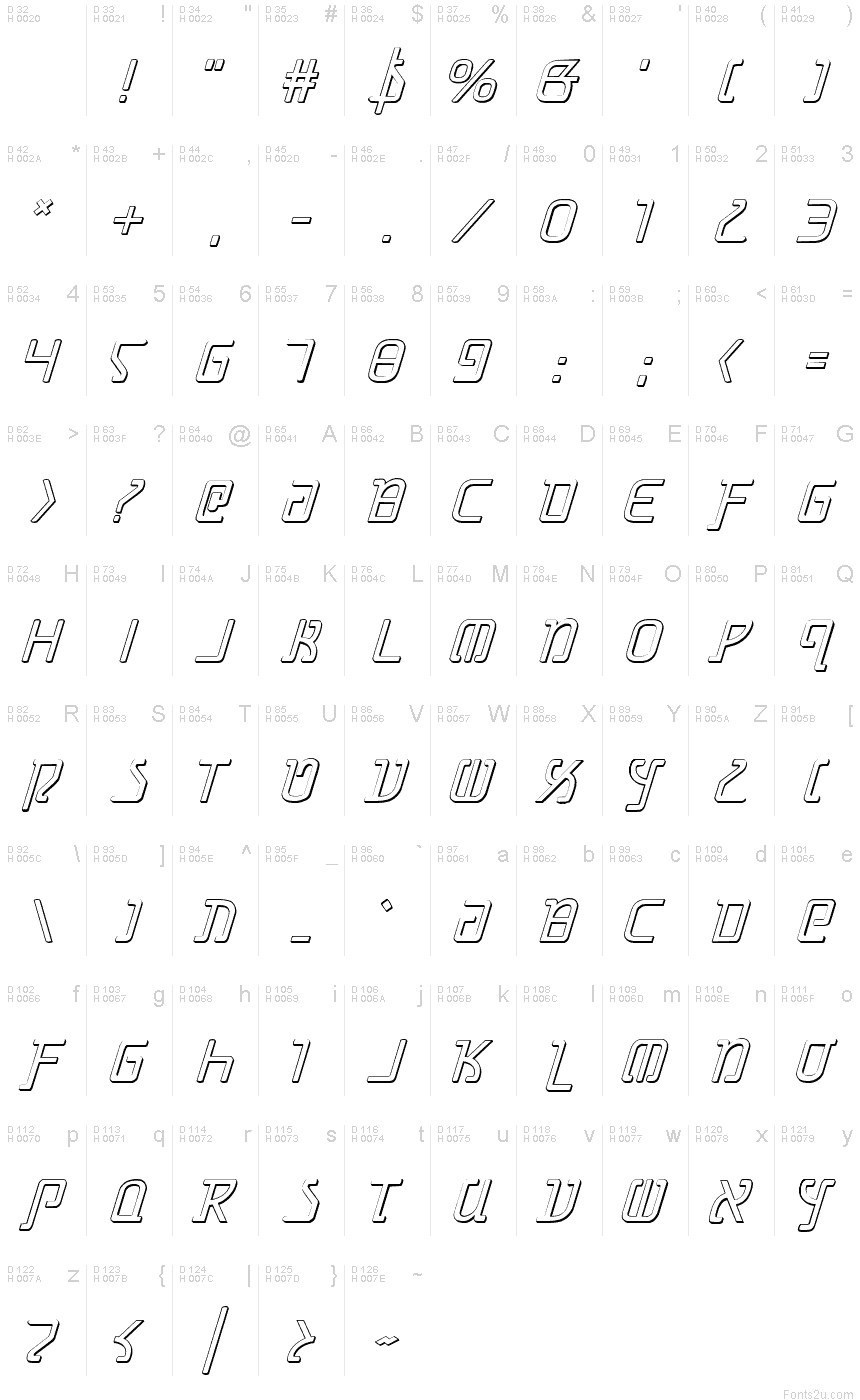
Grimlord Shadow Italic autorstwa Iconian Fonts to darmowy krój pisma typu display o konturowej budowie, z mocnym pochyleniem do przodu i retro-futurystycznym wyglądem science-fiction. Puste w środku litery, ścięte narożniki i kanciaste łuki tworzą opływową, mechaniczną sylwetkę.
Sporty motorowe i futurystyczna technologia to jej najbardziej oczywiste motywy. Konturowa konstrukcja sprawdza się na plakatach wyścigowych, w grafikach gier z automatów oraz w gadżetach science-fiction, gdzie litery mogą przypominać spersonalizowane emblematy pojazdów lub oznaczenia interfejsu. Najbardziej przekonująco wypada jako krój nagłówkowy w rozrywce skupionej na szybkości.